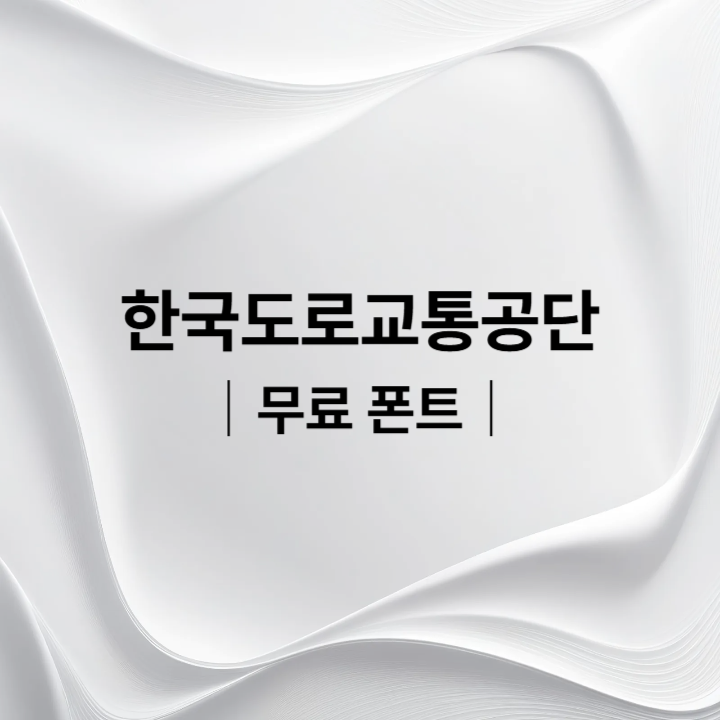
디자인 작업이나 공공기관 문서를 제작할 때 신뢰감 있는 무료 한글 폰트를 찾고 계신가요? 오늘은 공공기관에서 무료로 제공하는 한국도로교통공단 폰트(KOROAD)를 소개해 드리겠습니다.
도로교통공단체는 깔끔하면서도 안정적인 느낌을 주는 서체로, 공문서와 인쇄물은 물론 블로그 썸네일, 카드뉴스, 프레젠테이션 디자인에도 활용하기 좋은 무료 폰트입니다.
한국도로교통공단 폰트란?
한국도로교통공단은 교통사고 예방과 안전한 교통문화 조성을 위해 다양한 공공서비스를 제공하는 기관입니다. 기관의 정체성을 표현하고 국민과의 소통을 강화하기 위해 전용 서체인 도로교통공단체를 무료로 배포하고 있습니다.
도로교통공단체의 특징
1. 안정감 있는 디자인
도로교통공단체는 지나치게 화려하지 않고 균형감 있는 자소 구조를 가지고 있습니다. 덕분에 긴 문장에서도 가독성이 뛰어납니다.
2. 공공기관 이미지에 어울리는 서체
안전과 신뢰를 중요하게 생각하는 공공기관의 이미지를 담아 단정하고 정직한 느낌을 전달합니다.
3. 다양한 디자인 활용 가능
한국도로교통공단 폰트는 깔끔한 가독성과 안정적인 디자인이 장점인 무료 한글 서체입니다. 공공기관 특유의 신뢰감과 단정함을 표현하고 싶다면 적극 활용해 보시기 바랍니다.
특히 블로그 썸네일, 교육자료, 안내문 제작에 활용하면 전문적인 분위기를 쉽게 연출할 수 있습니다.